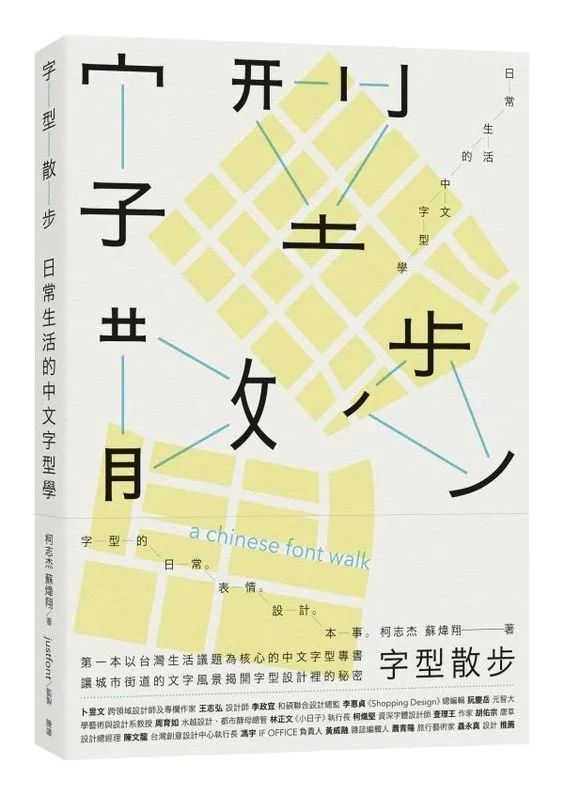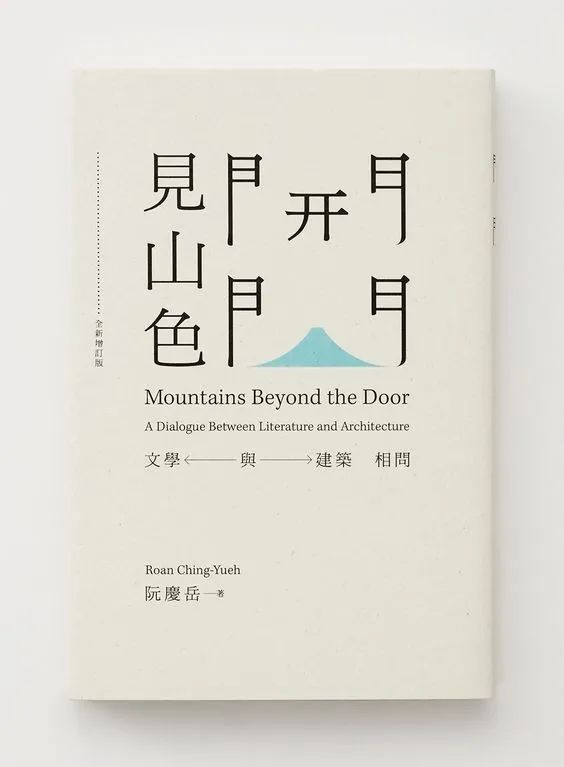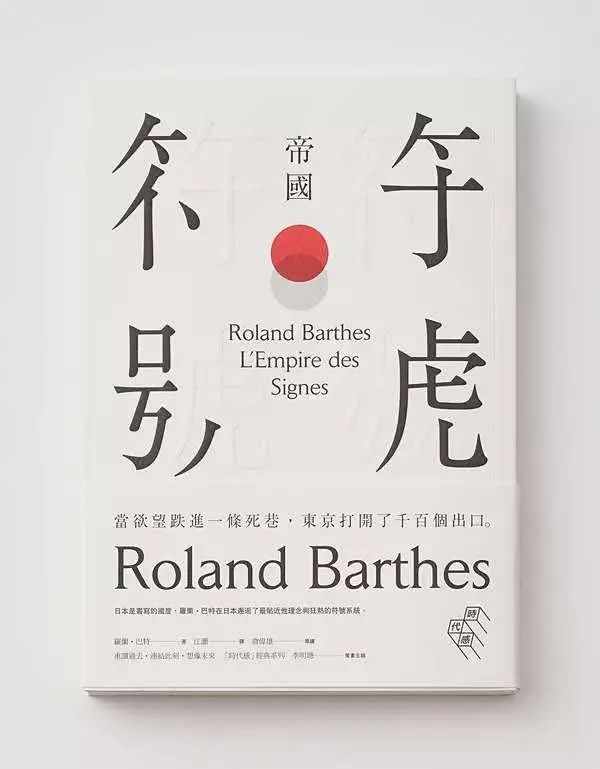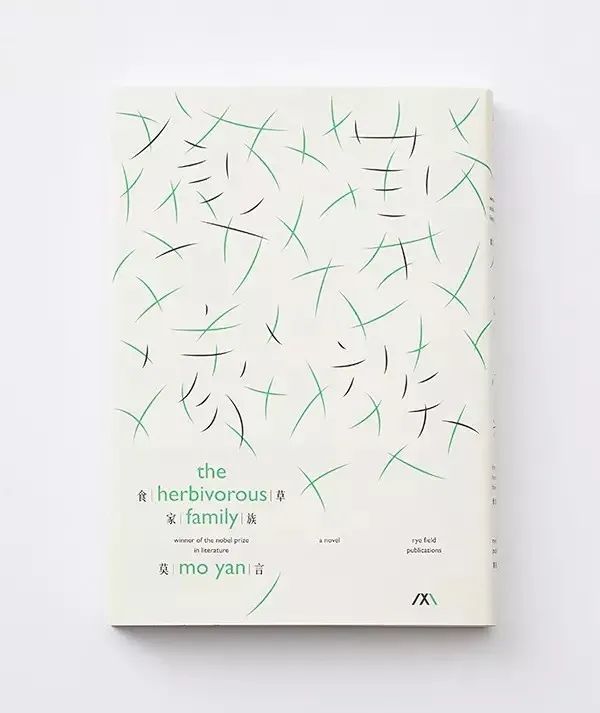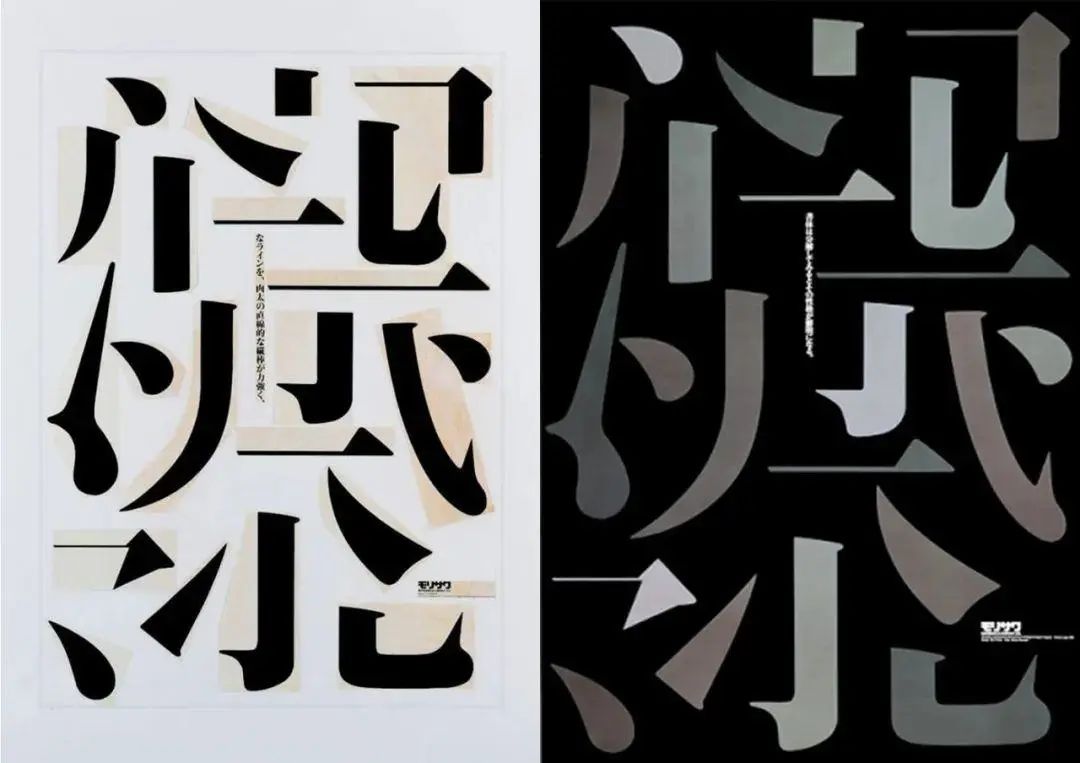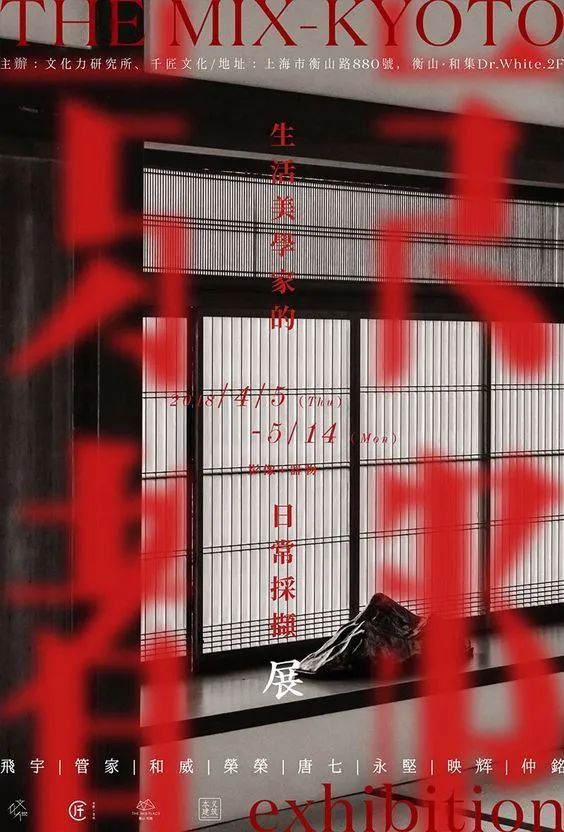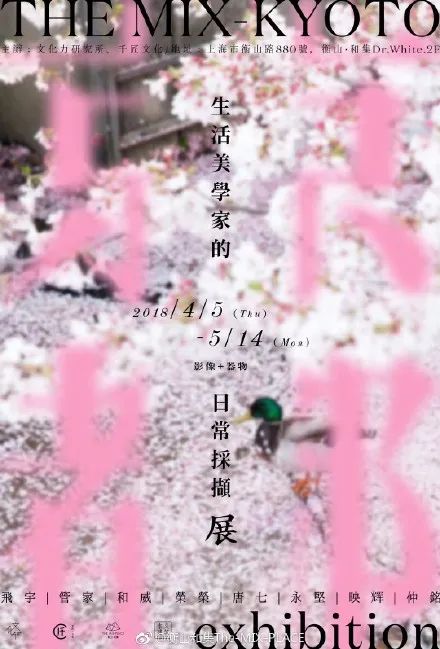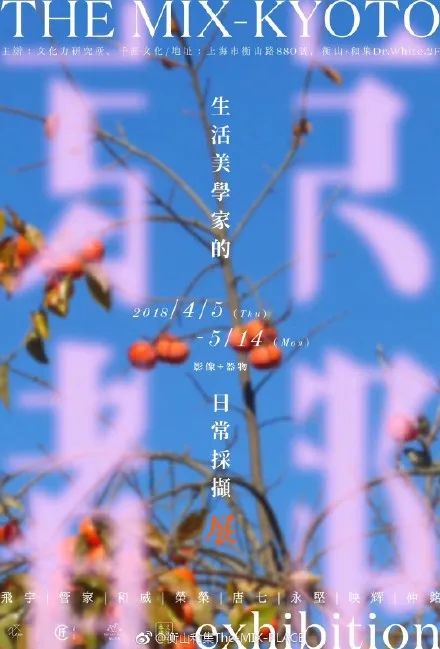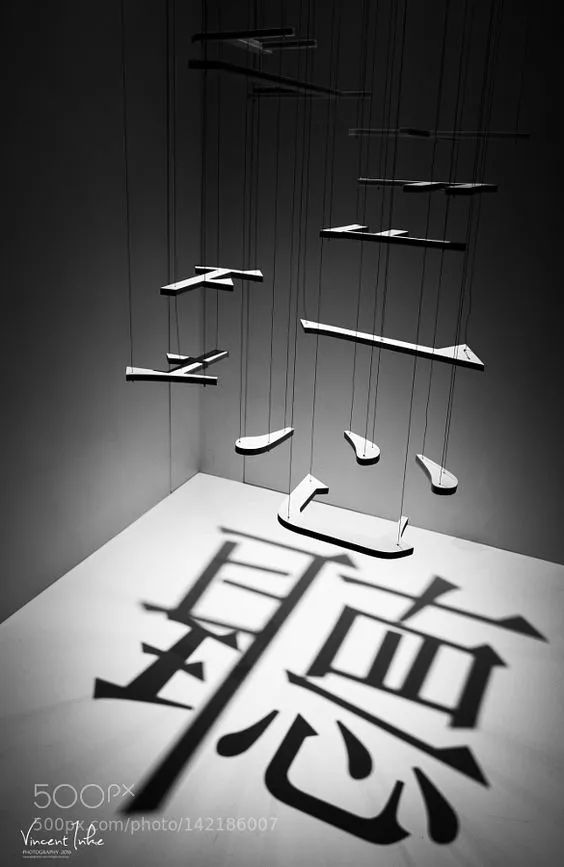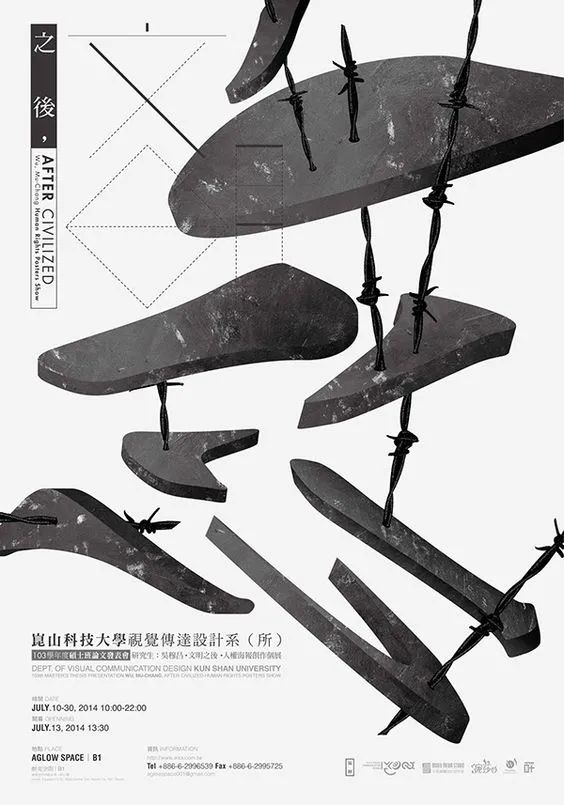
设计方法之汉字笔画解构
很多时候设计师在面对一个设计任务的时候,苦于缺乏素材,或是不知如何创作图形,今天分享一种超实用的设计手法,那就是将汉字的笔画进行解构、拆分和重组,运用到画面中,很多大师都喜欢运用这种设计手法,来一起看看这种手法的精彩案例吧!
王志弘的书籍封面设计
王志弘是华人设计师中首屈一指的平面设计大师,在他的书籍设计中,也常常可以看到将汉字笔画进行解构的手法,比如下面这本《字型散步》,将四个字的笔画拆开,然后在中间辅以细线连接指引,使字体的形散而神不散,同时在封面上形成了丰富的点线面元素,非常具有趣味性。
再比如这本《开门见山色》,利用汉字象形的特点,巧妙的将 “门” 字的笔画拆开,中间放入富士山的图形,巧妙的将这一意象传达了出来,同时也将书名的含义表达了出来,创意令人拍案叫绝!
下面这本《符号帝国》,从视觉效果上看,亦是对笔画进行了左右对称拆分,而细看其实左右两侧都是完整的汉字,只是巧妙的将字的一部分不印颜色,同时用凸起的工艺,形成若隐若现的视觉效果,同时兼具触觉感受,这些细节让一本书极具艺术感。
《食草家族》这本书的设计更为精妙,在看似随意确十分有秩序感的抽象化草丛中,将部分草组成了食草家族这四个字,值得注意的细节是,设计师并没有把所有字的笔画都设计成黑色,这样形成了一种若隐若现的视觉艺术效果。
小说《家变》的封面设计,王志弘将 “家變” 两个字进行了破碎化的处理,用解构和扭曲的汉字笔画营造出一种坍塌、破碎的氛围,将小说的主题体现的淋漓尽致!
田中一光《文字的想象力》海报设计
田中一光《文字的想象力》主题海报,将汉字的笔画打散重构设计而成,将宋体字笔画的魅力优雅地展现了出来,成为了经典。
下面这张《纽约字体艺术指导俱乐部》年度展海报,使用了和田中一光同样的设计手法,是对田中一光的致敬。
THE MIX-KYOTO
《生活美学家的日常采撷展》
THE MIX-KYOTO,《生活美学家的日常采撷展》系列海报,将京都二字拆分放置在海报中央,不仅统一了一系列海报的主视觉,同时将 ”京都开展”这一概念巧妙地表达了出来。
更多案例
汉字笔画解构的玩法还有很多,当你在面对一个设计任务时,如果没有合适的可用素材,不妨试试这种方式,当然不论如何进行解构,紧扣主题都是你要优先考虑的。